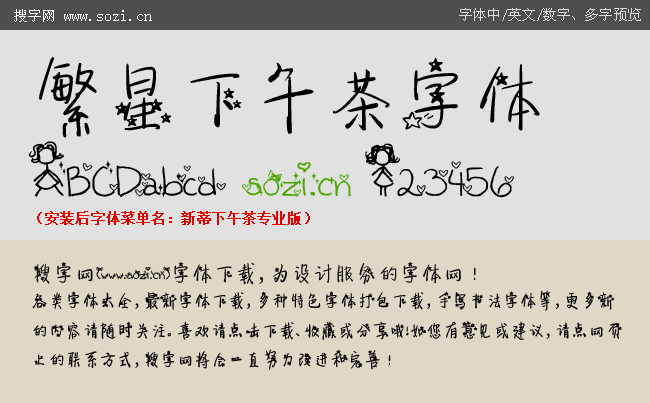
繁星下午茶字體
搜字網(wǎng)給大家提供一款書(shū)法風(fēng)格的字體下載。修改者給他起名為繁星下午茶字體字體,這款手機(jī)字體是以新蒂下午茶字體為原形,將字體的個(gè)別筆畫(huà)用星星圖案替換,新蒂下午茶字體是一款手寫(xiě)風(fēng)格的中文簡(jiǎn)體字體,非常有手寫(xiě)感,一些筆畫(huà)替換卡通圖案后更加可愛(ài),喜歡的朋友可下載收藏。